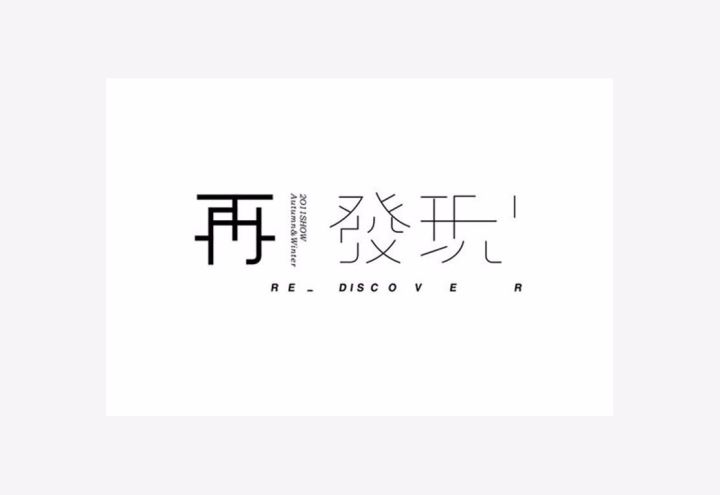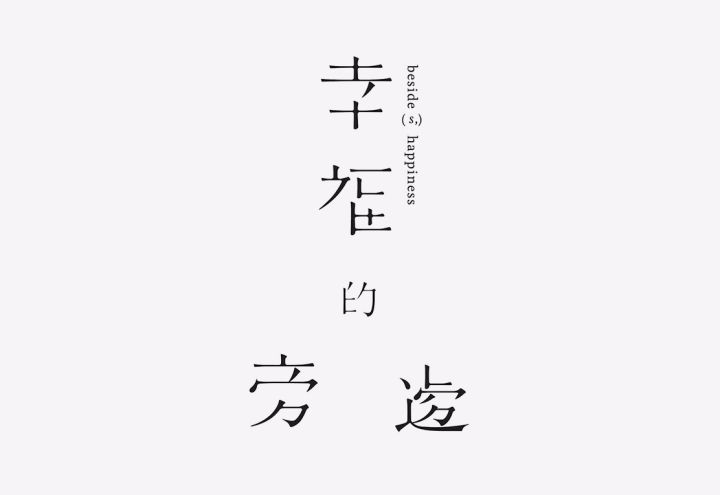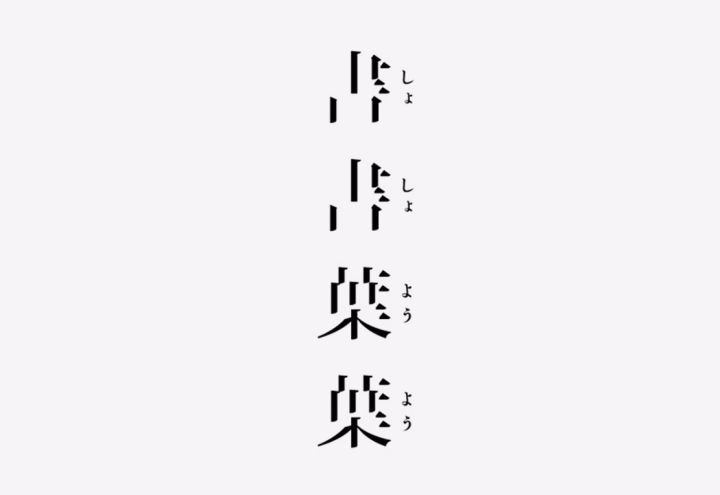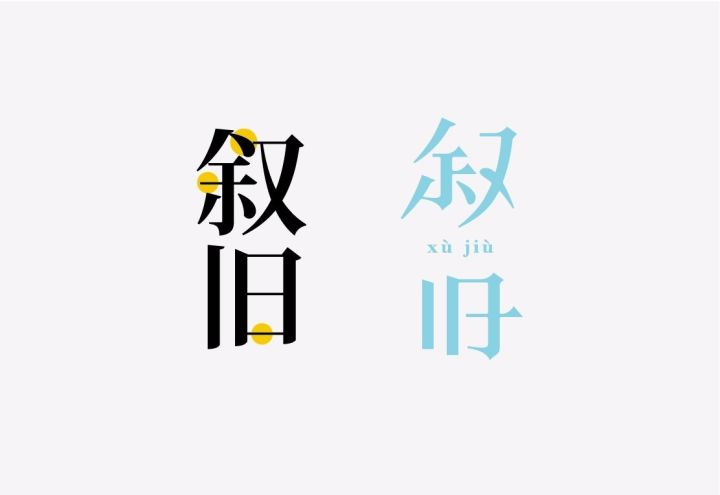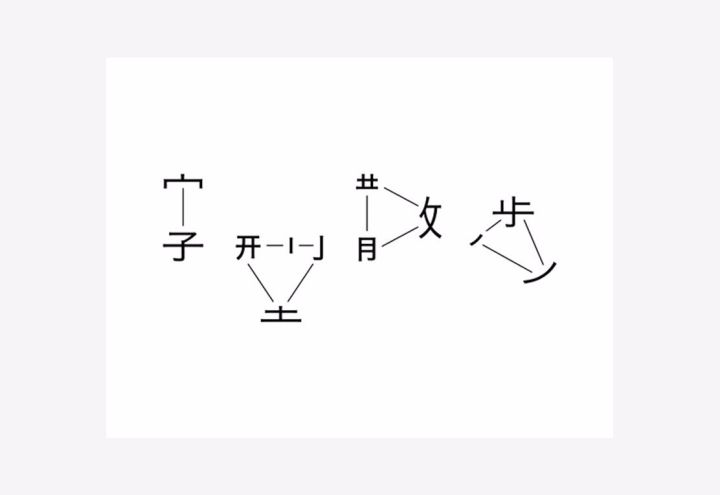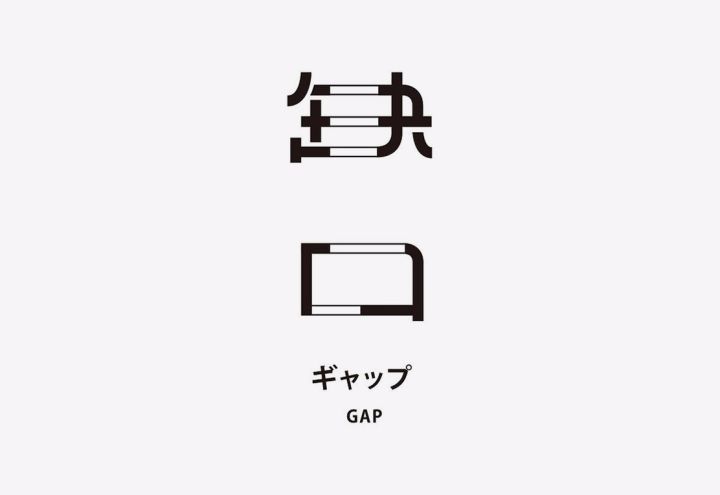
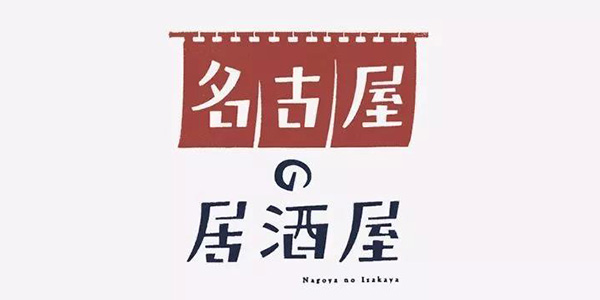
【干货】字体设计的断舍离
假期大家忙着游山玩水去远方,或是因为熟悉的地方没有风景。道理挪到字体设计中来,设计一款艺术字如果和平日常见的字体一样,那也就不觉得有什么特别,所以说想要让字体有足够的魅力与吸引力有必要用点“小手段”!
处理字体的“手段”有很多种,今天就和大家聊聊字体设计的断舍离,听名字挺诗意其实断、舍、离是字体设计中非常基础常用的三种不同的处理形式,三者和字体笔画有密切的联系,下面就具体看看这断舍离到底该怎么用!
一、断
两个字解释就是“断笔”,这里讲的断笔不是字体本身笔画与笔画之间自然的间断,而是刻意将本来相互连接的笔画进行裁切,完整封闭的笔画有了新的间断。这样做可以很大程度上产生新的空间秩序并打破原有字体的阅读节奏,结构空间会变得更加透气,断笔也会产生一定的层叠关系,普通的文字也就多了些层次和变化。
方法技巧
断笔可不是随随便便的裁切,一般是在两个相交的笔画处做断笔的处理。这里我们可以根据笔画的走向分为横断、竖断、斜断,叫什么无关紧要也不需要记牢,简单上个图大家区分一下便可。
通过此图也可看出横断的手法是最容易出效果的,也是平时使用最为频繁的。要注意这三种断法不是排他使用的,可以相互配合使用。
断面一般是有两种处理形式,一种是比较直接的平行处理,再一种是异型处理方式(如上图)。
其中图中的异形处理方法同上,只是断面做了斜切,和相邻的竖笔有一定的角度,当然如果你的笔画起笔收笔有弧度或是其形式,断面也可以相应的进行统一。
不论字体笔画是面构成还是线构成,都有可以进行断笔的处理,沉闷简单的字也可以变得透气活泼。
这组字的笔画比较简单,如果没有进行断笔处理的话就会显得比较平庸没特点。主要还是横笔做裁切,断面和竖笔的角度保持平行,断点的位置其实也是有规律的,都是在每个字的偏左的位置。
笔画即便是不规则的也可以做断笔处理。上图中的文字结构笔画都是比较轻松的,整体做了一个对角的断笔处理,断口大小、断面角度都有所不同,更符合整组字轻松的气氛。
需要注意什么?
试想一下如果把迷宫中的每个封闭的墙面都给通开,那么也就失去了迷宫的可玩性。在字体设计中要切记断笔勿贪多,如果把每个笔画都断开那么整个字定会七零八乱,要知道断笔起到的仅仅是一定的装饰作用。
二、舍
舍即是舍弃,再简单点说就是给字体做减法。汉字本身就是很复杂的图形,具有很强的辨识性,即使是舍弃其中的一两笔甚至更多也不会影响字体的识别性,舍的巧妙反而会让字体更具个性。
前面讲的”断“只是给字体动动小手术,”舍“就是在动大手术,它能够释放更多的留白空间,让字体更有想象空间和趣味性,即便是普通的字库字体,尝试舍弃其中一两笔也会发现效果果然不一般。
方法技巧
加法容易减法难,舍弃笔画是要有选择性的,有这样一个小规律:舍弃的笔画尽量不要选择影响字体外部轮廓的笔画,下面这个图会告诉你为什么。
同样的一组字,一个是用正圆遮挡内部笔画,一个是遮挡外部笔画留下同样面积的正圆部分,你会发现虽然两组字都能够被识别出来,但第二组的辨识要比第一组吃力许多,所以”舍内不舍外“显然要划算的多,当然汉字结构千变万化,一些比较常见常用汉字即使内外都舍弃一部分笔画也同样可以辨别,所以大家还是要一句不同的字形结构有选择性的进行取舍。
看个小例子,上面这组字有选择性的去掉横笔,但也有选择性的保留一部分横笔,仔细观察你就会发现其中的规律,舍弃的横笔大都是局内并不影响字体外部轮廓的,这样就能够在不影响识别性的前提下最大限度的删除“多余”横笔。
我们仔观察一组字的时候,眼睛就会不自觉的跟着汉字本身的书写笔顺进行阅读,所以在进行笔画的删减时还要注意:尽量不要删除连续的多个笔画,即便是内部笔画也是如此,保持字体笔画的连贯性也能够很大程度上保证字体的识别度。
宋体字本身具有很强的书香气如果舍弃部分笔画会多了份”仙气“,这组字就是非常典型的宋体字的舍弃笔画的处理形式,去掉横笔部分但保留字脚也是为了保证外部轮廓的完整性。
上面两组字只是简单的舍弃一两笔,配合其他的一些变化,也能够起到画龙点睛的作用。所以说舍绝不以“多”取胜,而是比“巧”。
三、离
“离”像是断和舍的中和,其目的是产生空间距离,再直白一点就是笔画的拆分重构。都说距离产生美,这一点果然没错!重点是笔画间有了距离后字体会更具“图形化”,似乎是除了字义本身更能表达难以言表的情感。
方法技巧
首先是距离,其实只要能够保证画面内字体的完整性距离不是问题,最怕的是距离有了但联系没了,这样就像一盘散沙不能成型。
这组字距离是不小,几乎可拆卸的部分都增加了间距,好在有线条的引导让每个部分能够紧密相连,我们在做字体设计的时候其实少有这么多笔画同时进行拆分,多是以局部的拆分为主。
和上组一样的处理形式,如果拆分力度大、距离远就需要一定的(线段)辅助,这样就很好的保证拆分部分的独立性,字体的整体性也不会受到丝毫破坏。
其次比较重要的一点就是局部笔画的选取技巧。一般是选择一些撇、捺、点之类的笔画做分离,相对横竖是比较典型的笔画;拆分后其中单字的稳定性也要适当的注意。
还是看个小例子,观察上图其实拆分的笔画就是“逝”字的走之旁,距离并不太远但呈现渐行渐远的趋势,也是契合这组字的本意。
面对不同的字形结构和风格需求,我们总会有不同的应对方案,断、舍、离不是一种固定的模式,三者间是可以相互协调应用的,除了灵活应用更要结合自己的理解和造字的习惯,多看多练同样少不了。
今天所讲的这三种字体的处理形式虽说都很常见,但有些小伙伴在实际操作中总会有些不够肯定,希望这篇小分享能够帮你梳理的更清晰,做起字来更轻松!